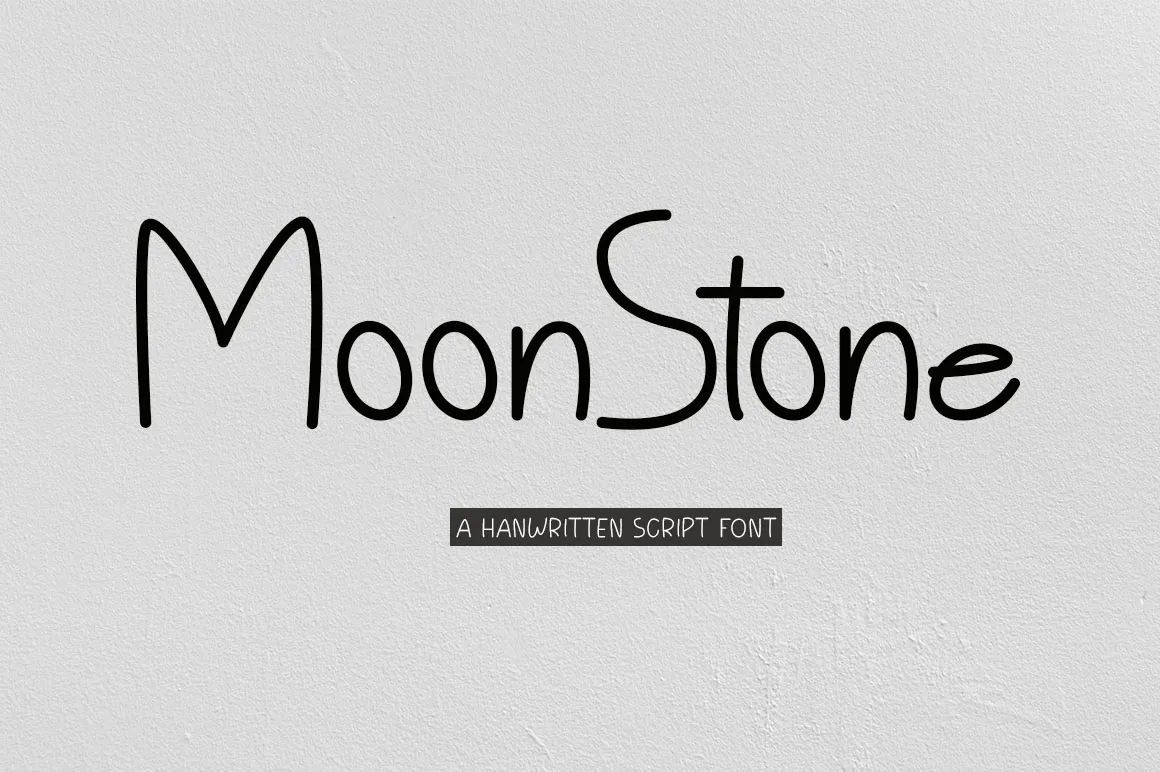
Essa é uma fonte escrita a mão linda e encantadora, perfeita para quem busca uma escolha elegante para seus projetos digitais. Suave, romântica e cheia de bom humor, essa font pode transformar cada ideia em um trabalho de arte real. Experimente esta font bela e descubra suas inúmeras variações. Eles vão encantá-lo e transformá-lo em criador de arte digital. O ‘MoonStone Font’ é uma ótima adição para qualquer projeto que você está desenvolvendo.
Designer: Muhamma Zamroni